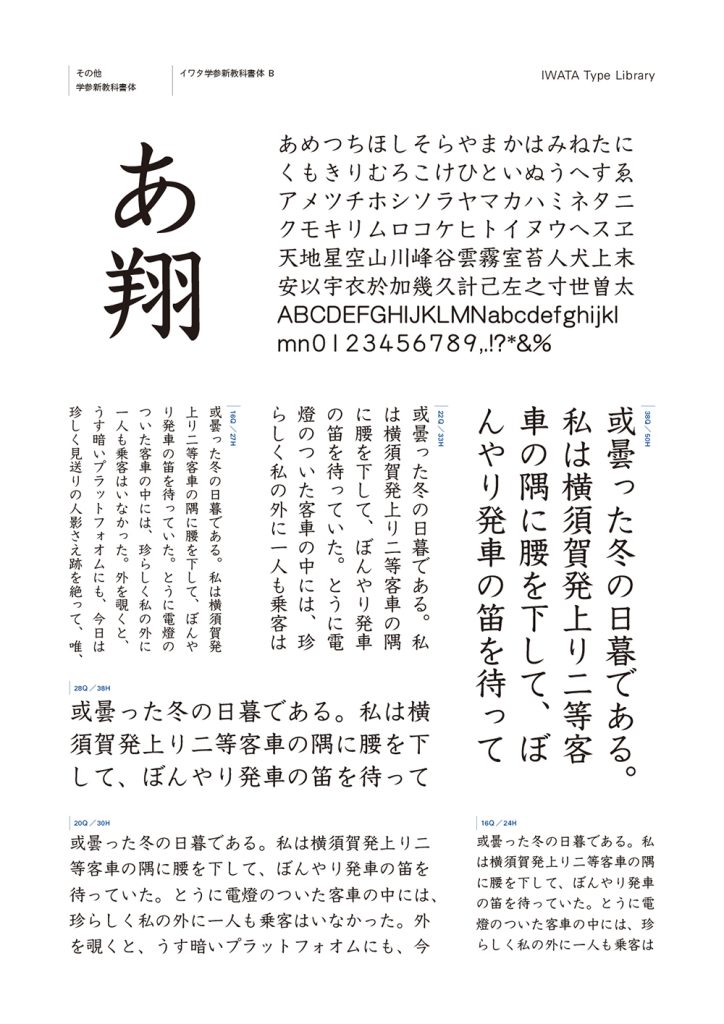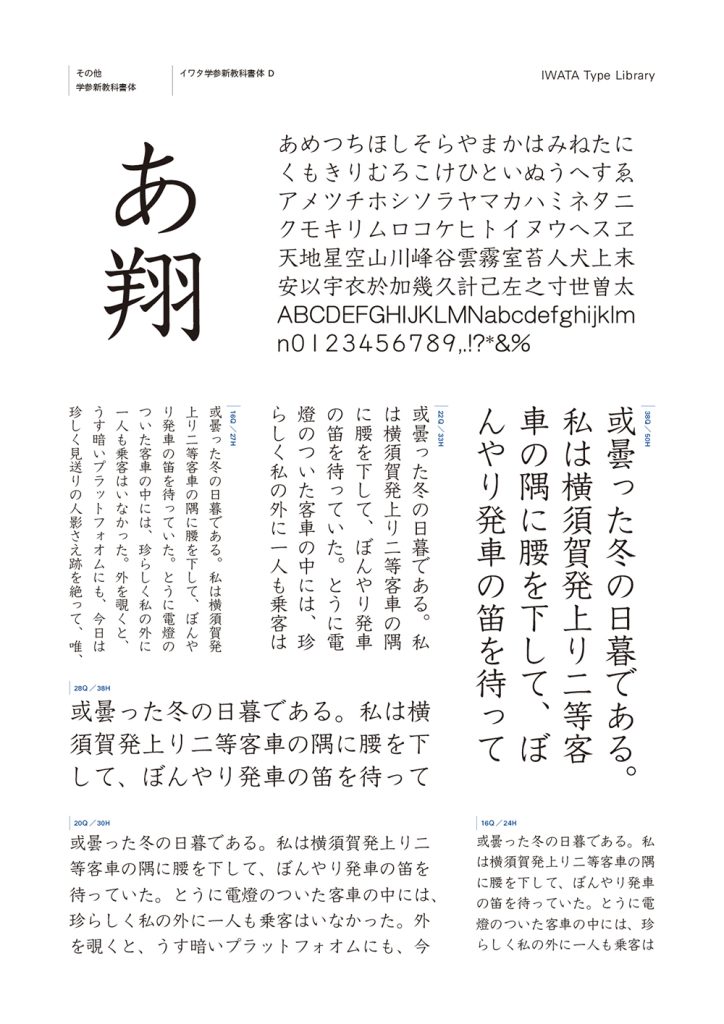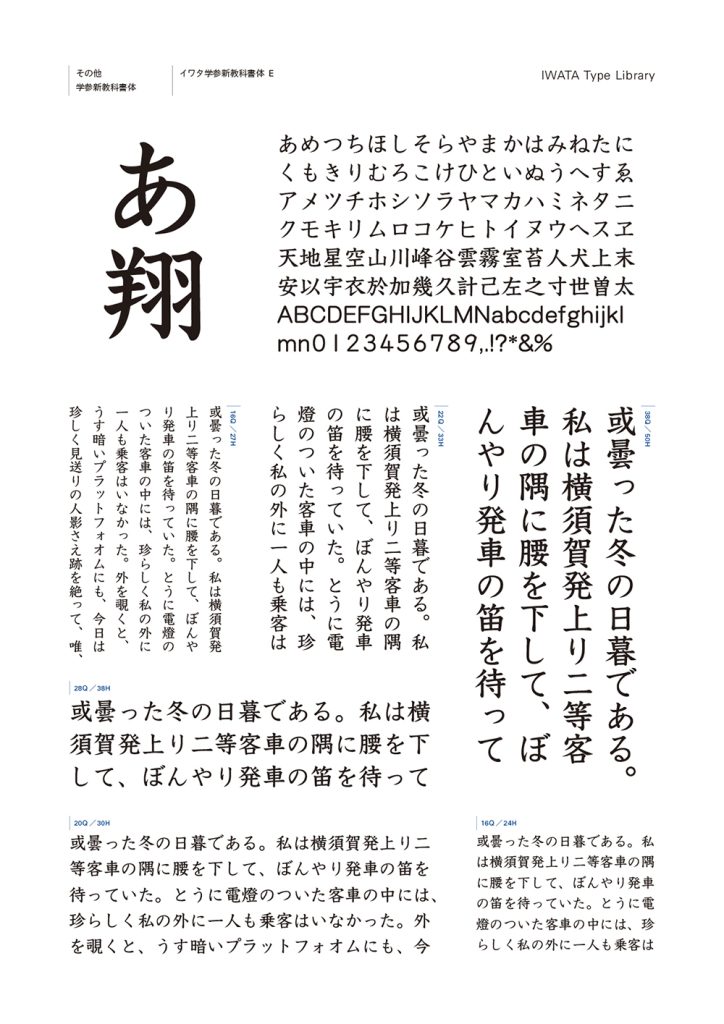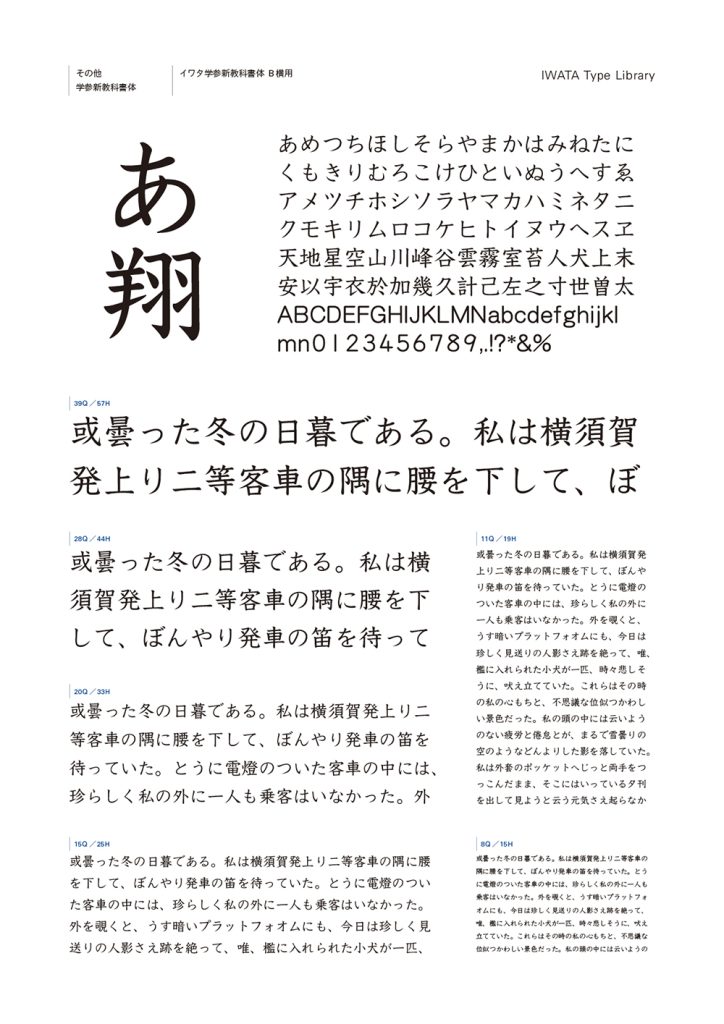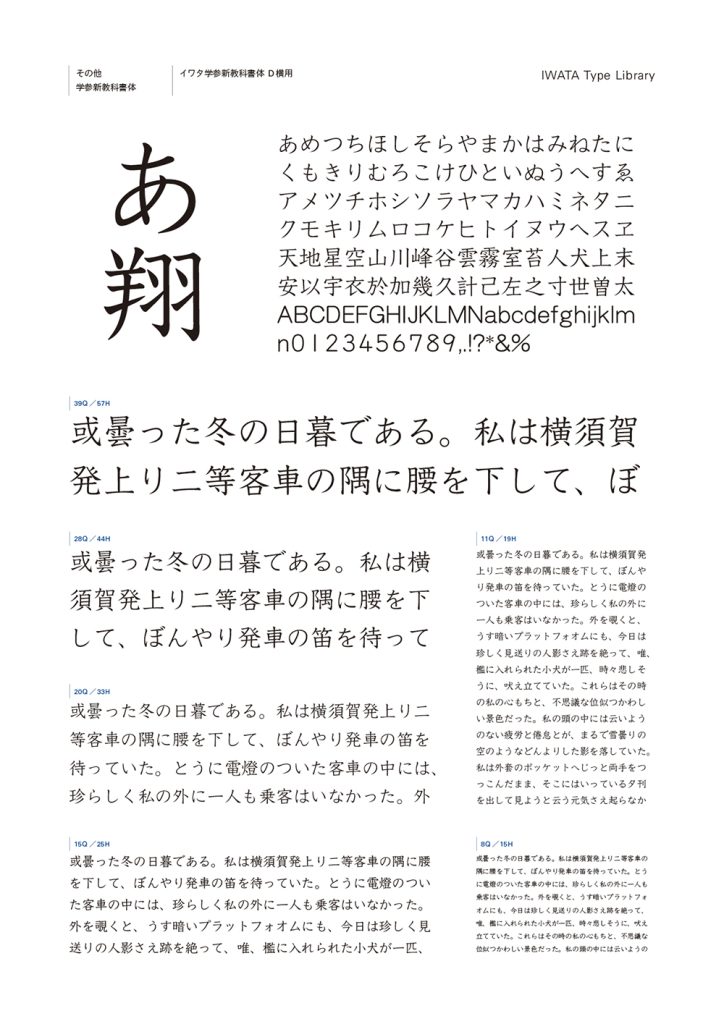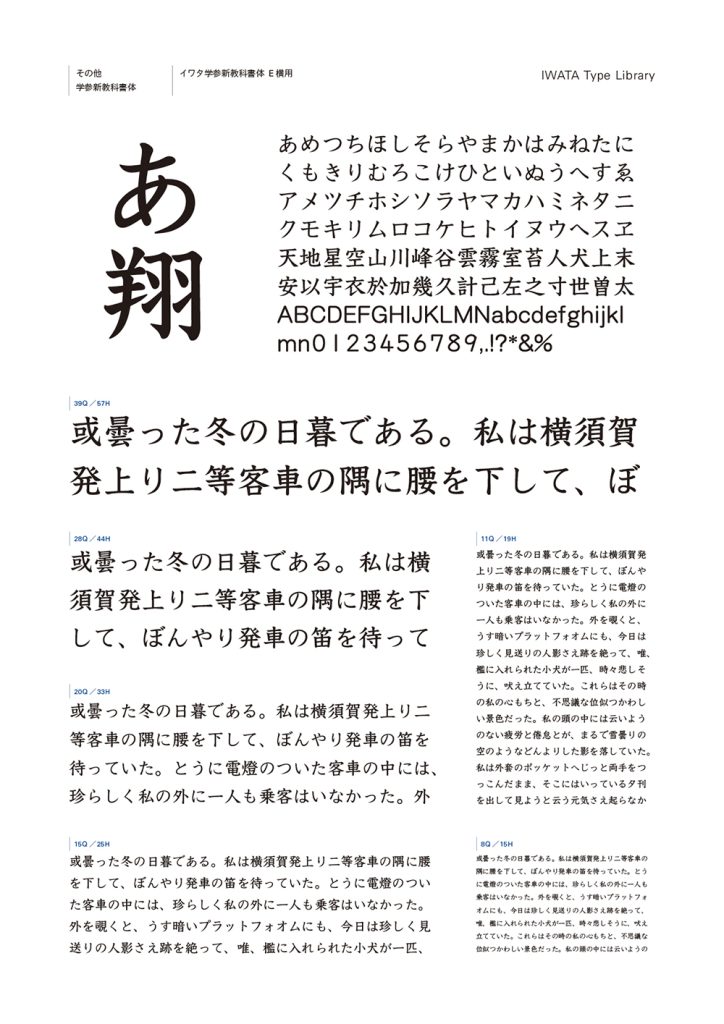
半世紀以上にわたる教科書体の伝統を受け継ぎつつ、現代の硬筆の書きぶりや電子デバイスへの対応を考慮して開発された新しい教科書体です。
UDフォントの開発で培ったノウハウを活かして見やすさと読みやすさを向上し、品位と美しさを兼ね備え、子どもだけでなく大人にも快適に読めるデザインです。
紙媒体だけでなく、デジタル教科書やデジタル学習参考書など、教育の現場で幅広く活用できます。また、横組みに適した「横用」デザインも用意されており、多様な使用方法に対応する書体です。